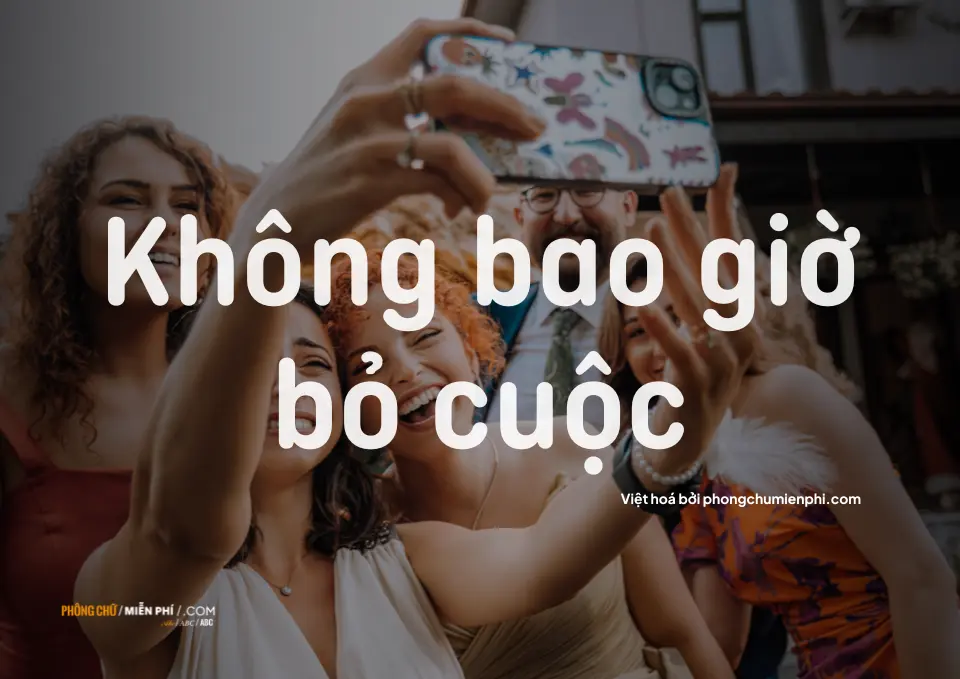
Tên font: Font Việt hoá Ciutadella Rounded Bold
Font Việt hoá PCMP Ciutadella Rounded Bold được việt hoá bởi phông chữ miễn phí.
Họ phông chữ Ciutadella Rounded là một họ phông chữ sans serif cổ điển, đơn giản và gọn gàng, với các cạnh mượt mà để mô phỏng việc in ấn cổ điển.